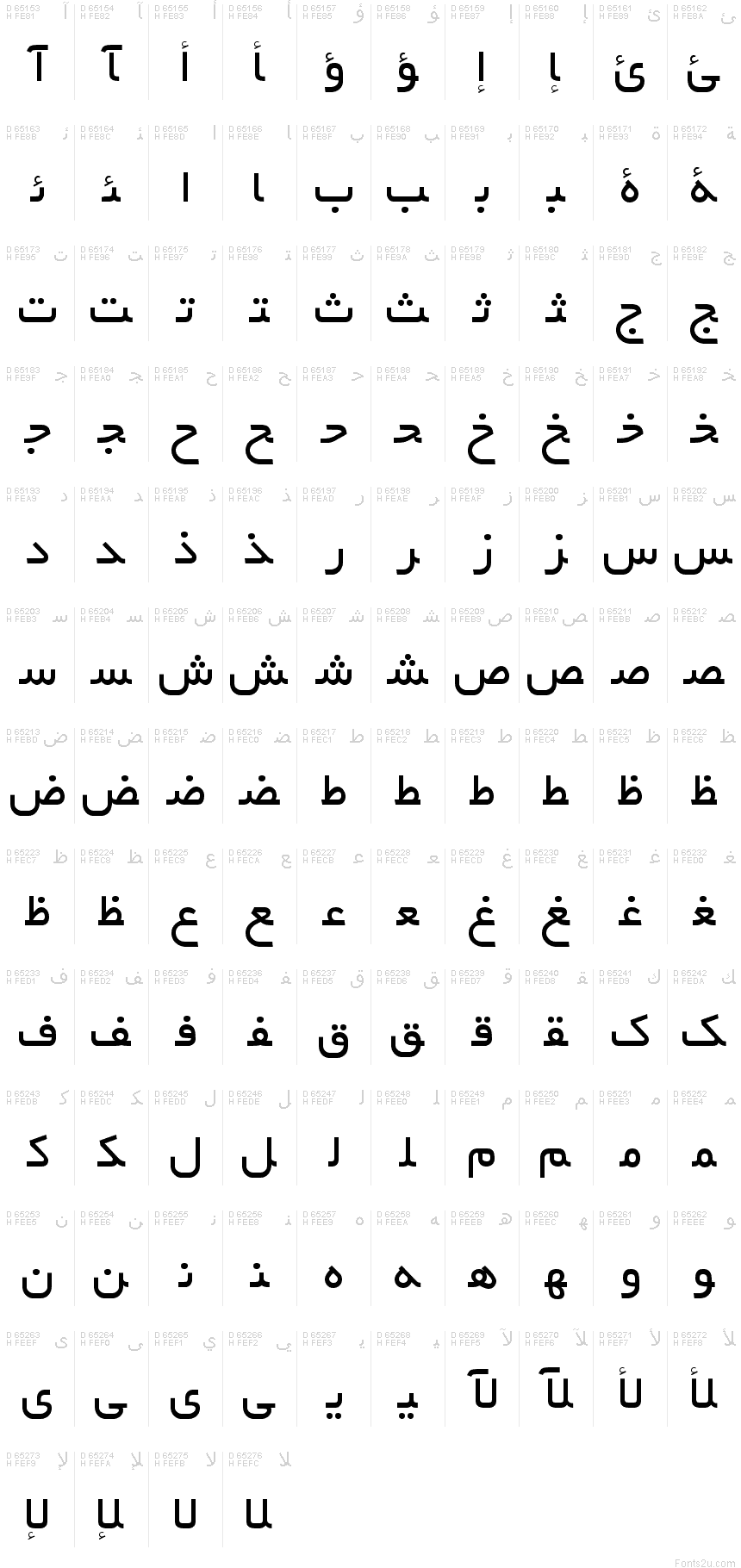
B Yekan, da Borna Rayaneh, é uma fonte árabe moderna, sem serifa e gratuita, com um tom calmo e contemporâneo. As letras parecem compactas e suaves, com um movimento arredondado e um peso uniforme que confere à escrita um toque prático e urbano, em vez de caligráfico.
Isso a torna uma escolha natural para rótulos de interface, embalagens, subtítulos editoriais, cartazes e sinalização, onde você deseja que o texto árabe pareça atual e direto. Como é uma fonte gratuita, também funciona bem em títulos e peças de branding curtas, já que as curvas contidas mantêm a escrita limpa e composta em tamanhos maiores.